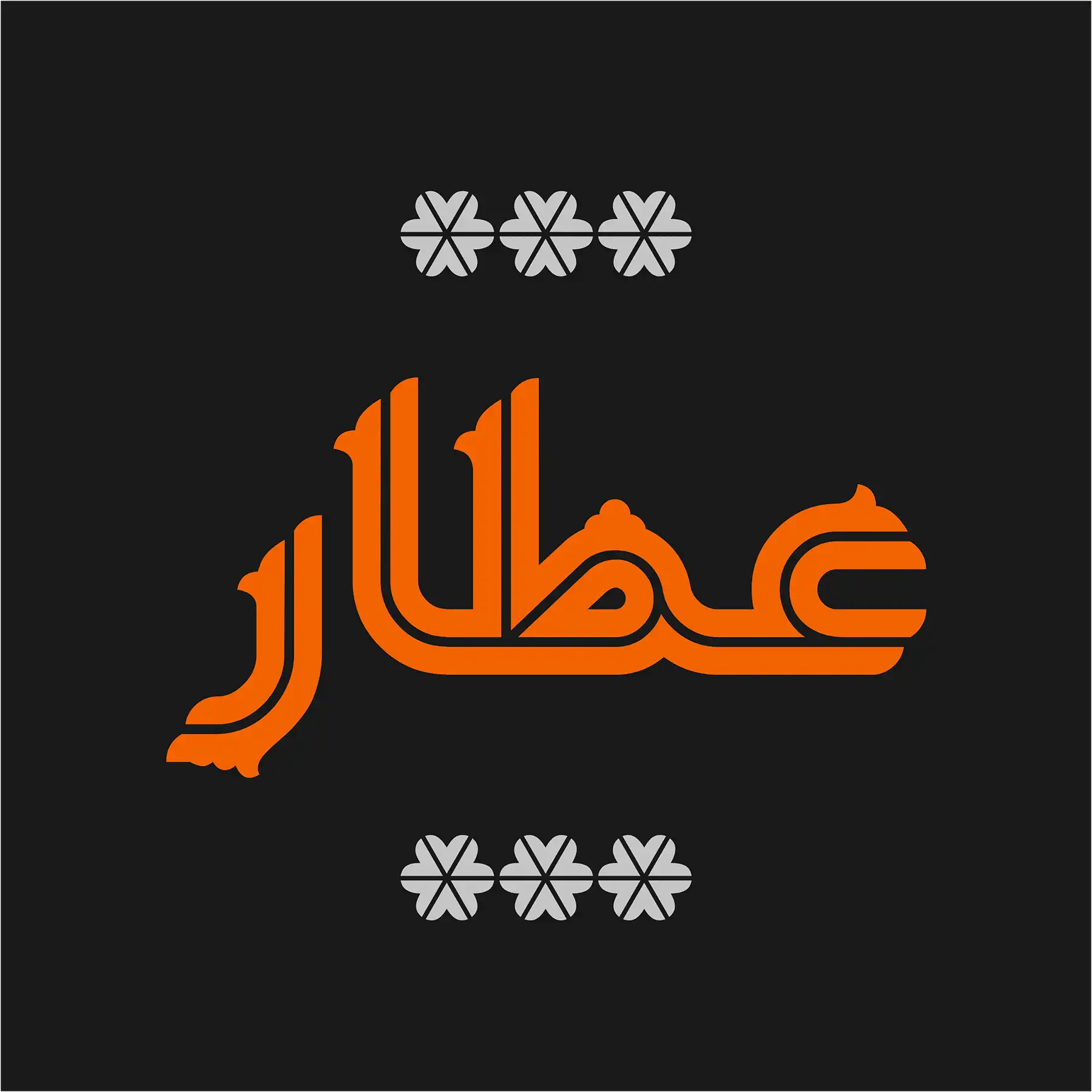
اگر به دنبال فونتی هستید که هم هندسی و مدرن باشد و هم اصالت ایرانی را در خود داشته باشد، فونت یکتا (Yekta) یکی از بهترین انتخابها برای شماست. این تایپفیس نمایشی با ترکیب سبک In-line و تزئینات گرافیکی الهامگرفته از نقوش اسلیمی، ظاهری منحصربهفرد پیدا کرده است.
ویژگیهای منحصربهفرد فونت یکتا
فونت یکتا یک تایپفیس هندسی و نمایشی است که در آن خبری از سادگیِ صرف نیست. طراح این فونت با ترکیب هوشمندانه خطوط داخلی (In-line) و تزئینات گرافیکی، شخصیتی دوگانه به آن بخشیده: از یک سو هندسی، منظم و مدرن، و از سوی دیگر گرم، تزئینی و ایرانی.
تزئینات بهکار رفته در حروف، حالوهوای نقوش اسلیمی و معماری ایرانی را تداعی میکنند — اما نه به شکلی سنتی و قدیمی، بلکه با زبانی مدرن و امروزی. همین ویژگی باعث شده فونت یکتا برای پروژههایی که نیاز به هویت ایرانی دارند، انتخابی بینظیر باشد.
فونت یکتا برای چه کاربردهایی مناسب است؟
- طراحی پوسترهای فرهنگی و هنری: تزئینات اسلیمی این فونت، آن را برای پوسترهای جشنوارهها، نمایشگاهها و رویدادهای فرهنگی ایدهآل میکند.
- لوگوتایپ و برندینگ: اگر برند شما هویتی ایرانی دارد، یکتا میتواند گزینهای عالی برای لوگوتایپ باشد.
- طراحی جلد کتاب و آلبوم موسیقی: برای آثار ادبی، تاریخی و موسیقی سنتی ایرانی، این فونت جلوهای خاص ایجاد میکند.
- تیتر و سرتیتر: بهدلیل ماهیت نمایشی، در اندازههای بزرگ بهترین جلوه را دارد.
- کارت دعوت و اقلام تشریفاتی: برای کارت عروسی، دعوتنامههای رسمی و مراسمهای خاص.
ترکیب فونت یکتا با سایر فونتها
فونت یکتا یک فونت نمایشی (Display) است و برای متنهای بلند مناسب نیست. پیشنهاد میکنیم آن را با فونتهای سادهتر و خوانا ترکیب کنید:
- برای تیتر: فونت یکتا
- نوع فونت: نمایشی (Display) — هندسی تزئینی
- سبک: In-line با تزئینات اسلیمی
- مناسب برای: تیتر، پوستر، لوگو، برندینگ فرهنگی